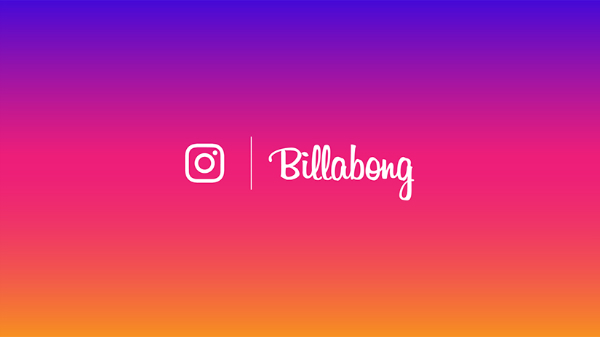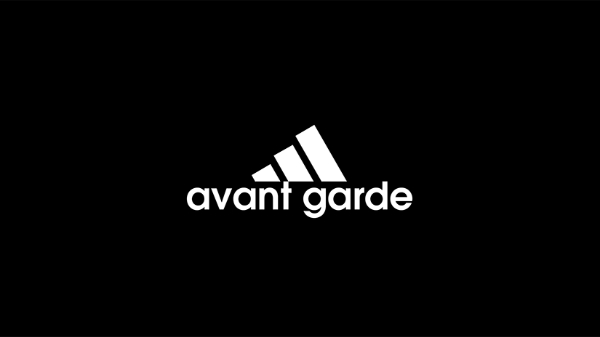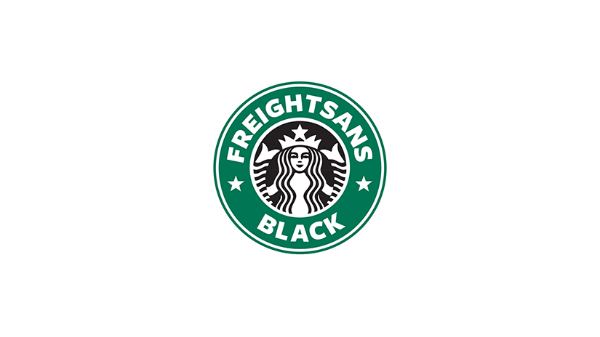
Logofonts es un proyecto del diseñador italiano Emanuele Abrate que profundiza en los logos de algunas de las marcas más conocidas y revela qué fuente tipográfica usan, original o modificada para la ocasión.
“A través de su diseño cualquier fuente tipográfica tiene la capacidad de comunicar sensaciones, valores y estados de ánimo”, dice Emanuele en su proyecto Type Talk! “Las fuentes pueden hablar, y es importante saber qué dicen para elegir la fuente que mejor se ajusta a lo que se quiere comunicar.”